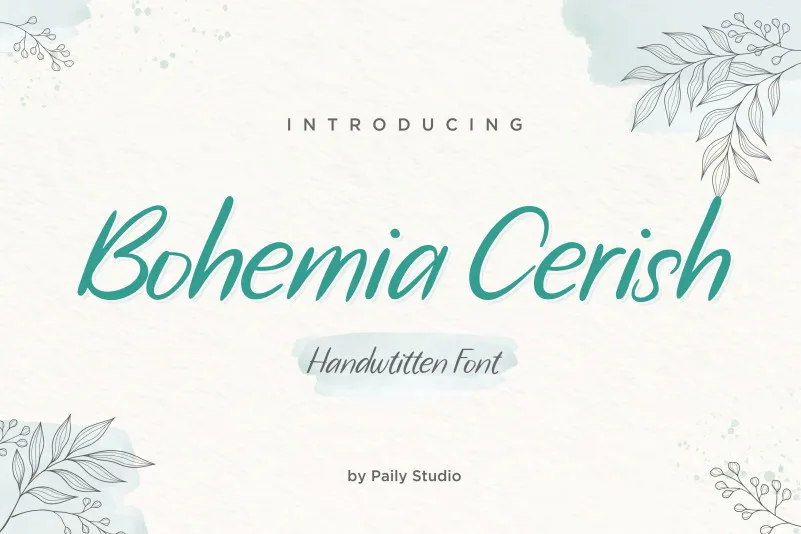
Bohemia Cerish Font – Download Grátis
A Bohemia Cerish Font é uma elegante caligrafia ideal para projetos onde a personalidade se torna fundamental. Suas linhas delicadas e cores suaves permitem que designers criem designs envolventes, tanto para aplicativos profissionais quanto para um estilo mais casual. Seja para criar identidades visuais vibrantes em logomarcas e materiais de marca, ou para adicionar um toque único aos cartões de visita e convites de casamento – sua caligrafia tem o poder de transformar qualquer projeto em uma obra-prima. Suas linhas fluidas e tonalidades suaves permitem que designers criem designs agradáveis tanto para aplicações profissionais quanto para um estilo mais despojado. Seja na criação de materiais visuais vibrantes em logomarcas, identidade visual ou convites de casamento – sua caligrafia tem o poder de transformar qualquer projeto num ato de arte. Com aplicabilidade em diversos tipos de projetos e um design refinado que transmite personalidade com facilidade, a Bohemia Cerish Font é uma escolha inteligente para designers buscando trazer a beleza da escrita à vida dos seus materiais visuais. Seja ele para criações profissionais ou para adicionar um toque singular aos cartões de visita e convites de casamento – sua caligrafia será o elemento diferenciador do seu trabalho, transformando-o em uma verdadeira obra-prima.